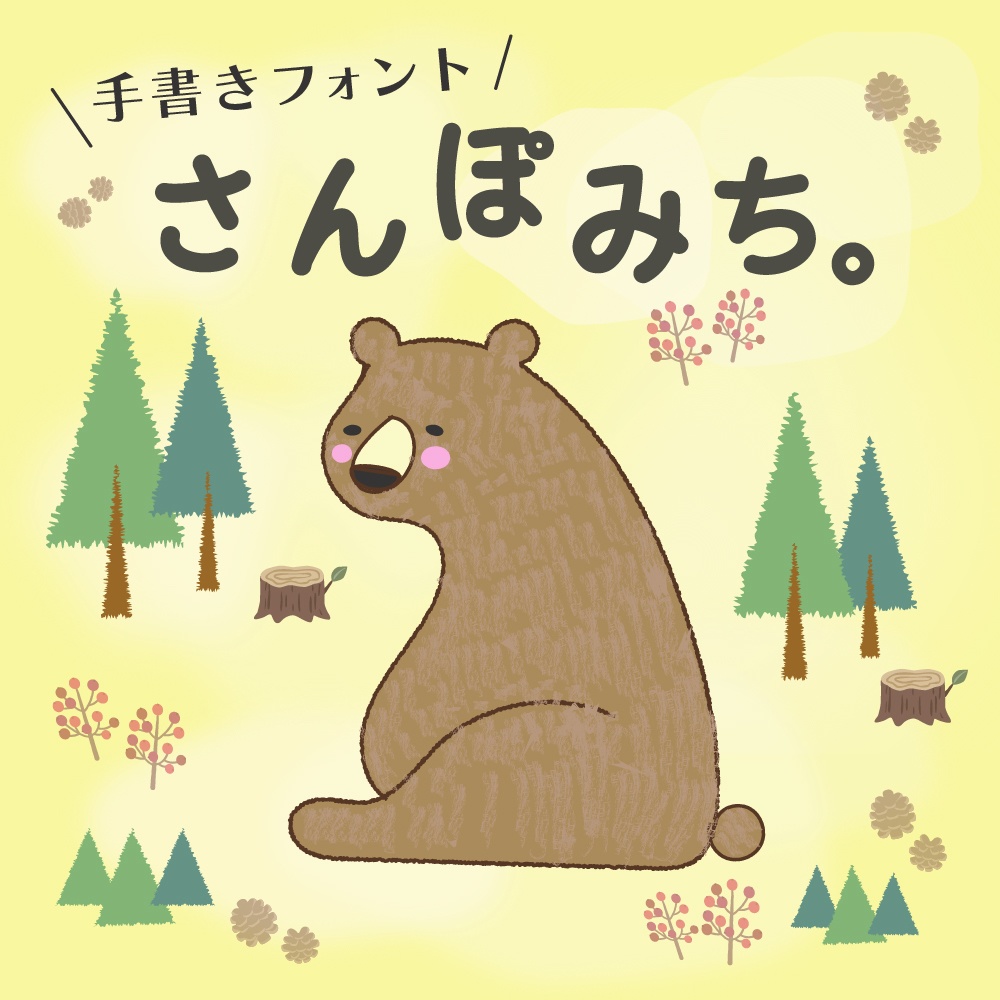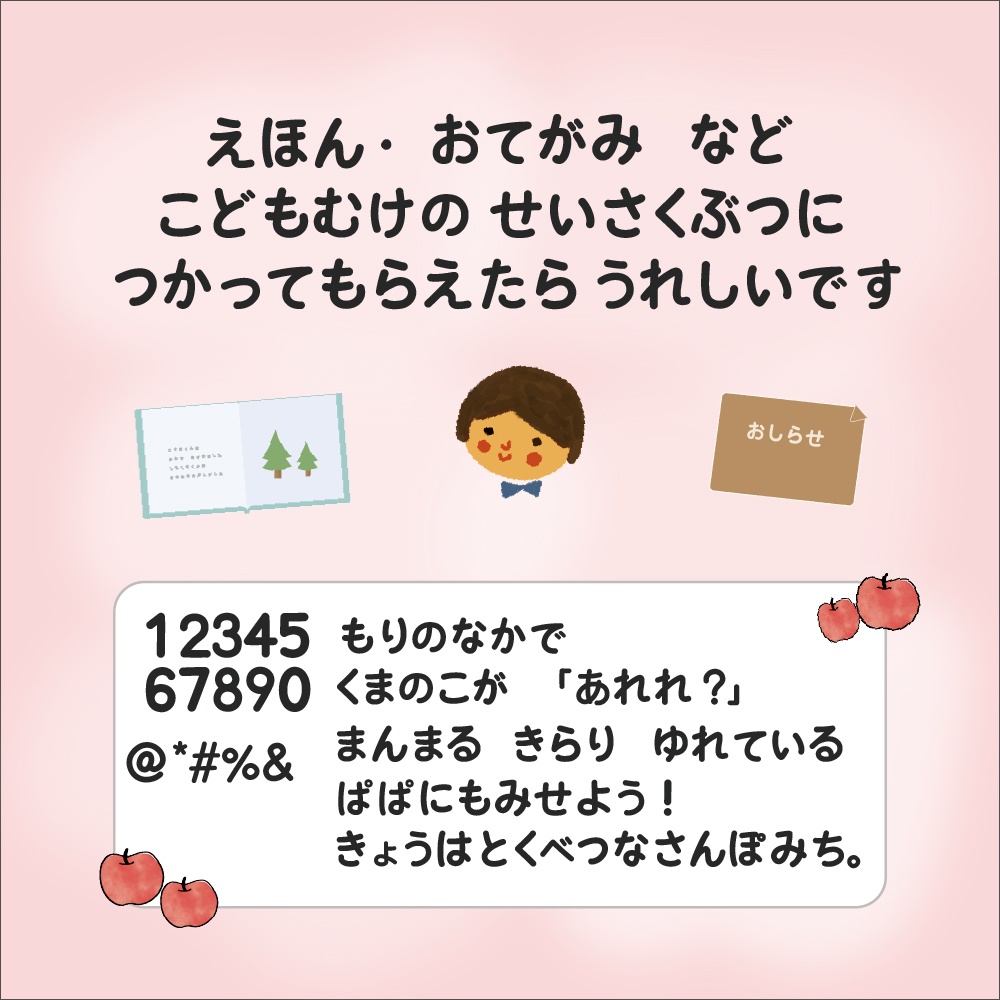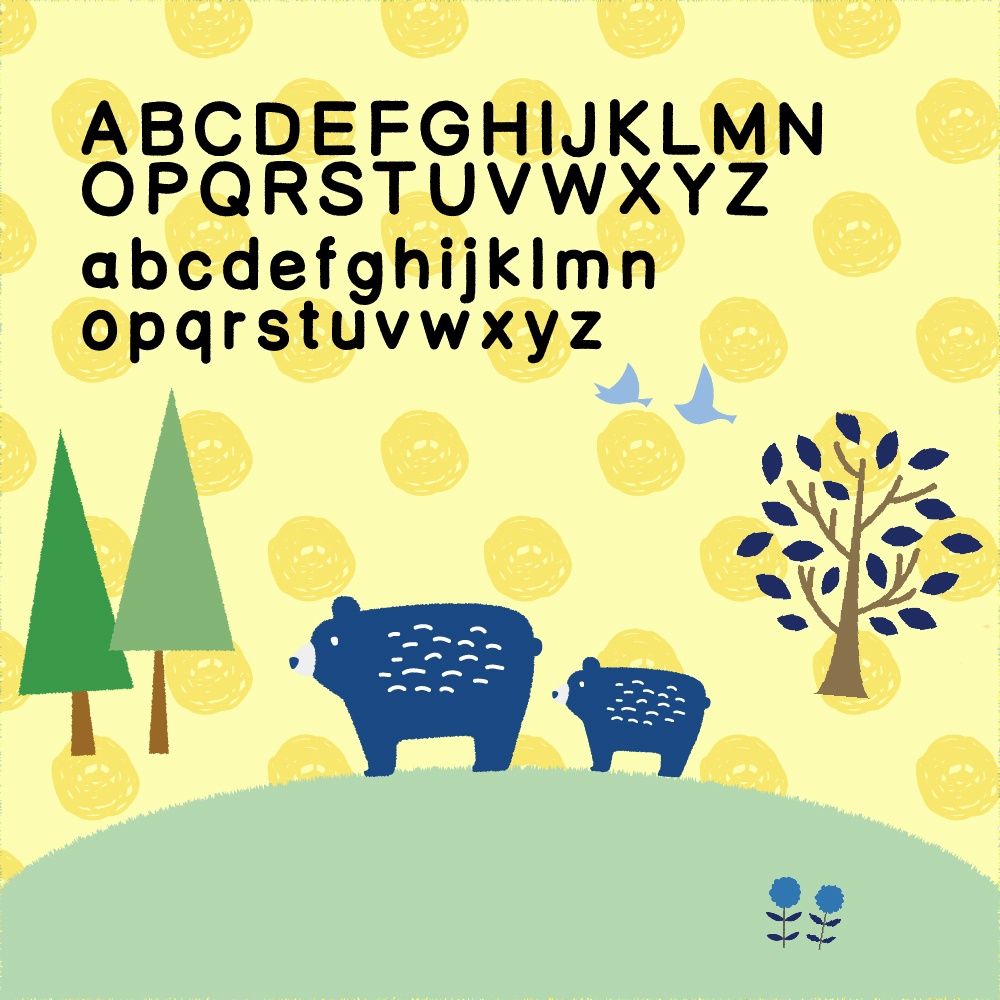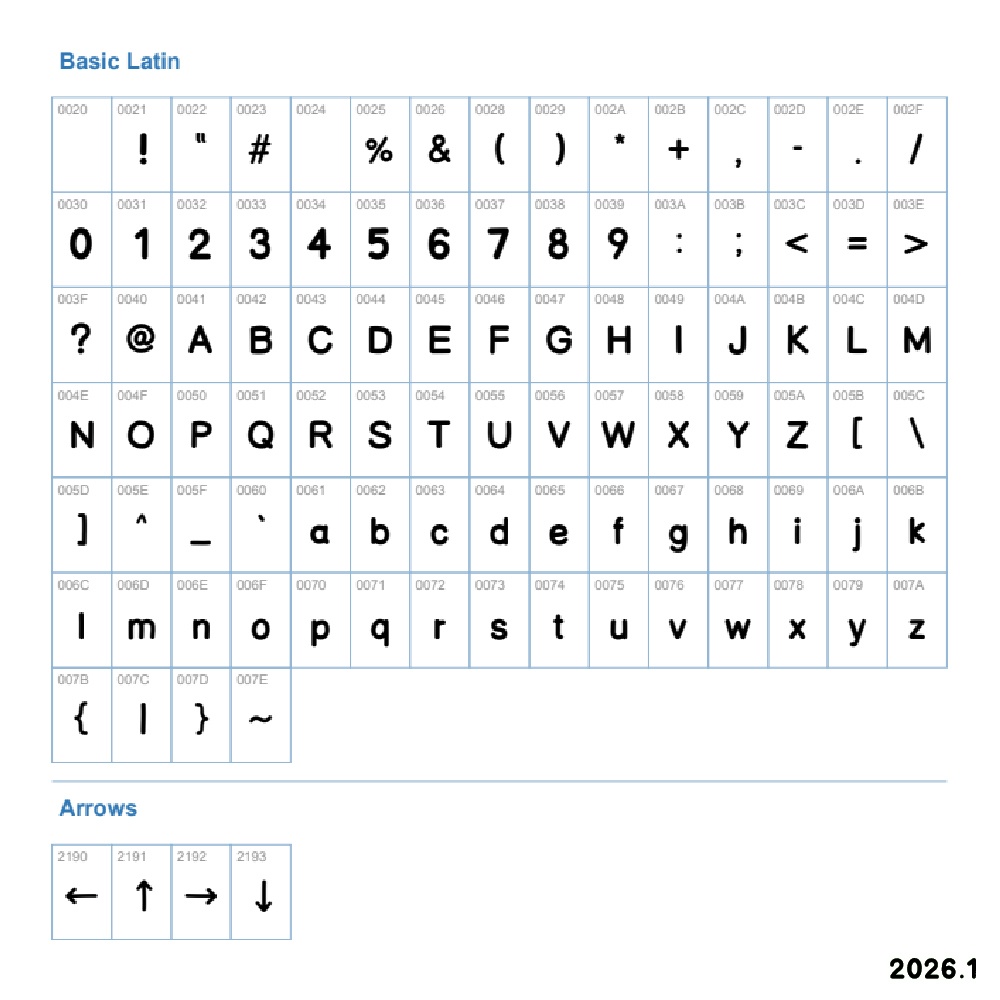
さんぽみち。日本語フリーフォント
丸ゴシックの横画を少し右上がりにした手書きひらがなフォント 読みやすさはそのままに、手書きのほっこり感で創作物を引き立てます 【仕様】 ・アルファベット・ひらがな・数字・記号 ・ファイル形式:ttf 【OKなこと】 ・商用・非商用どちらでも利用OK ・画像・動画・印刷物・SNS投稿など、自由に使えます ・絵本・ハンドメイド作品・グッズ制作にも使用OK ・クライアント案件で使うのもOK 【NGなこと】 ・フォントデータそのものの再配布・転売 ・自作フォントとして偽っての配布 ・フォントデータを抜き出して素材として再配布 ・公序良俗に反する使用 【免責事項】 フォントのインストールや使用によって発生したトラブル・不具合・損害などについては、制作者は責任を負いかねます。 初めてのフォント制作のため、環境によっては予想外の表示ズレや不具合が起きる可能性があります。 お手持ちの環境でご確認の上、ご自身の判断でご利用ください。 【その他】 フォントの仕様変更・アップデートを行う場合があります。 その際は販売ページでお知らせします。